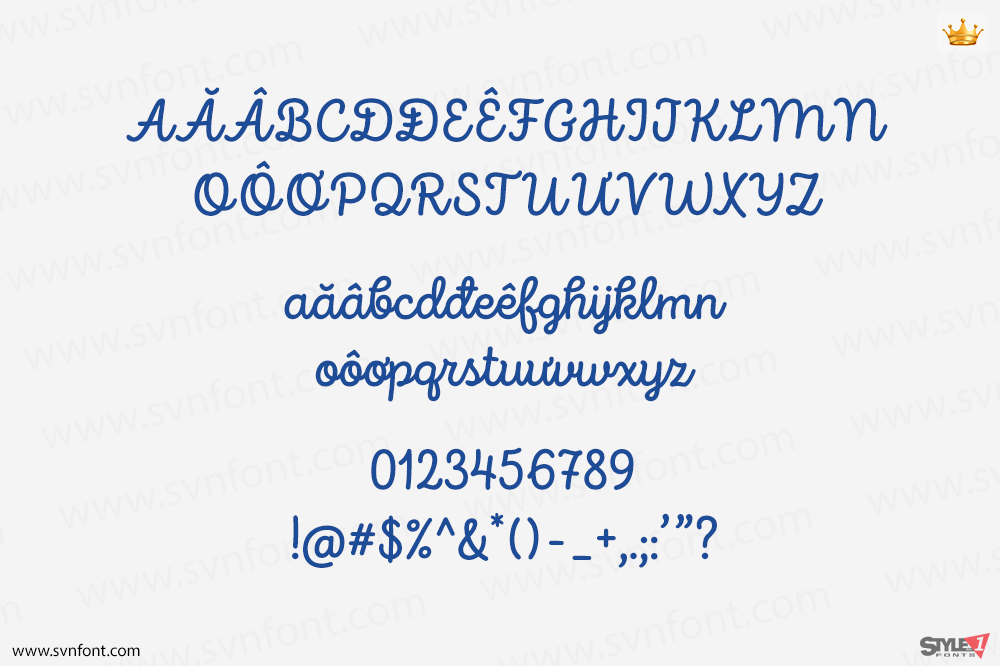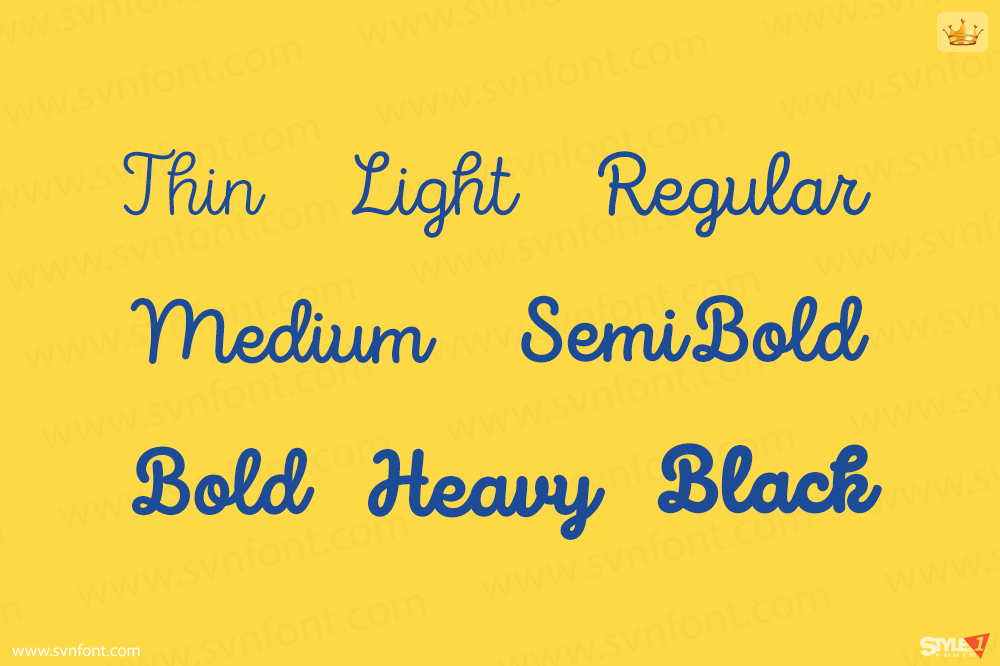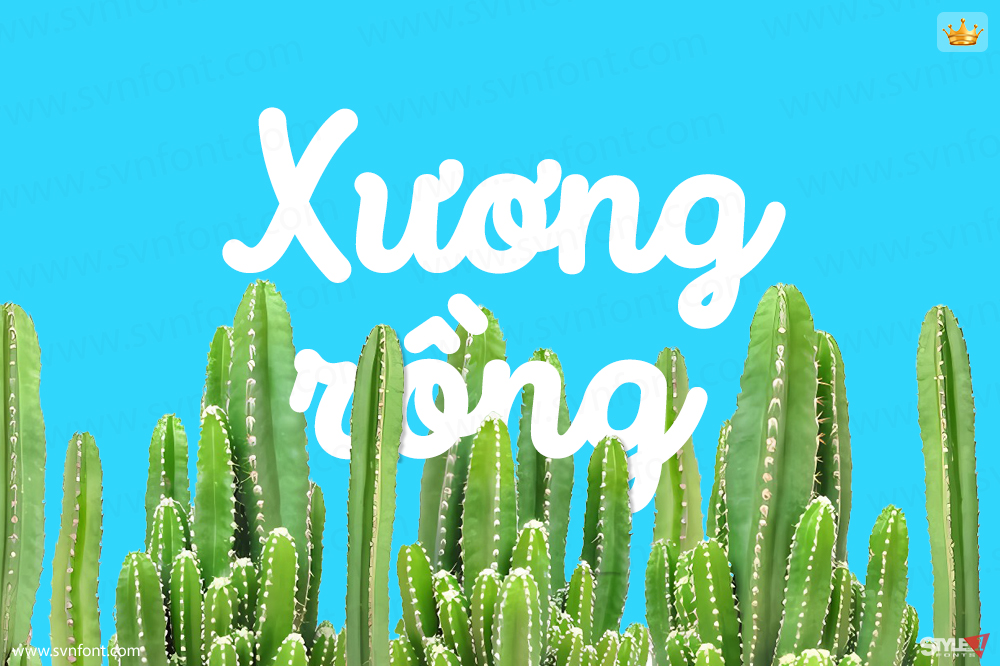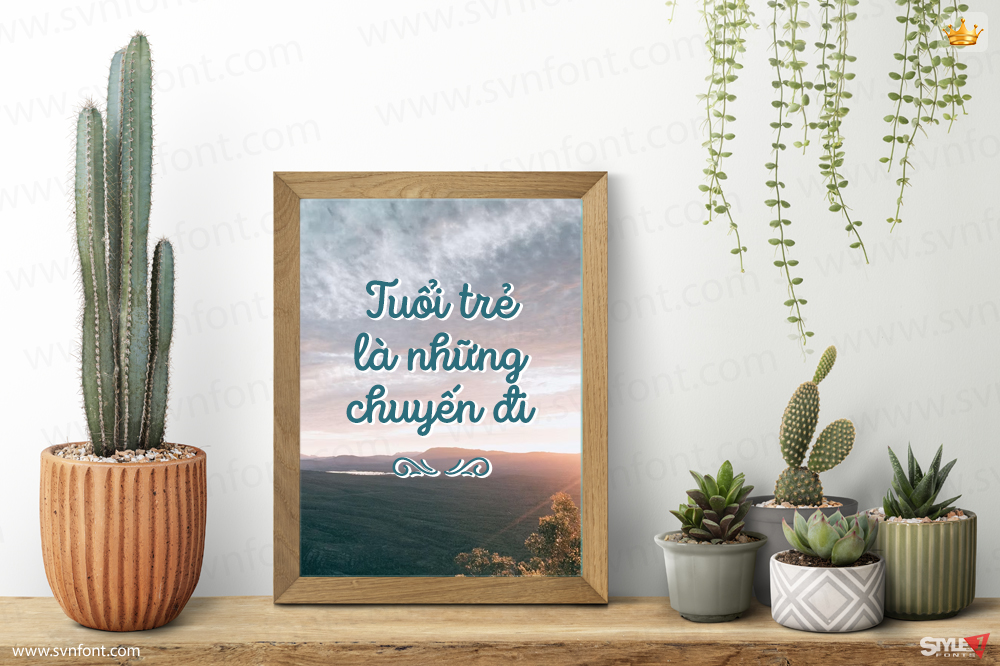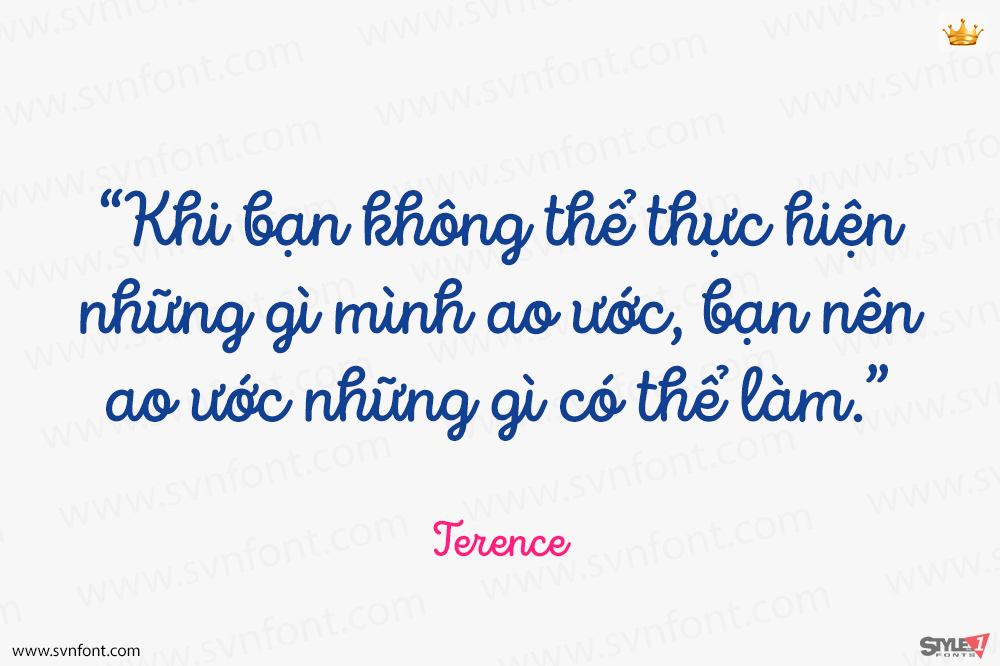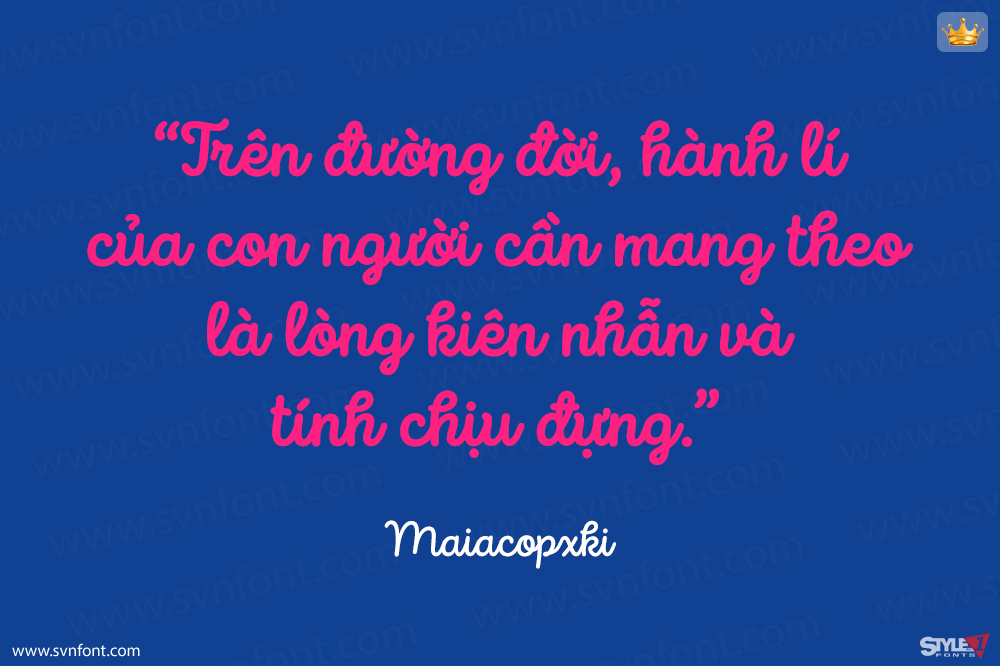
Intro Script mang trong mình những ý tưởng về sự trỗi dậy, đổi mới và tự do vô điều kiện. Là một phiên bản cập nhật và mở rộng của họ phông chữ Intro Rust, bản thân nó được phát triển từ hệ thống kiểu chữ Intro nổi tiếng, Script đi kèm với 8 độ dày khác nhau và vô số tiện ích và tính năng bổ sung để bạn tùy chỉnh. Chúng bao gồm 3 phông chữ bổ trợ với các từ, họa tiết và thậm chí cả biểu ngữ được làm sẵn, vì vậy bạn có thể thổi luồng gió mới vào dự án của mình. Bộ phông chữ này bao gồm một số lượng lớn các chữ ghép và chữ thay thế theo ngữ cảnh, bao gồm cả phiên bản chữ thường và chữ hoa, cũng như các biến thể vị trí. Các biến thể vị trí cho phép các ký tự kết nối ở các điểm khác nhau và giúp bạn tránh các khoảng trống không cần thiết, dẫn đến quy trình làm việc hiệu quả và dòng chảy tự nhiên hơn. Với khả năng hỗ trợ ngôn ngữ rộng rãi và nhiều tính năng OpenType, vẻ ngoài thân thiện, thủ công của Intro Script khiến nó trở thành một lựa chọn phù hợp và linh hoạt cho mọi thiết kế.
Nhà thiết kế: Ventsislav Dzhokov